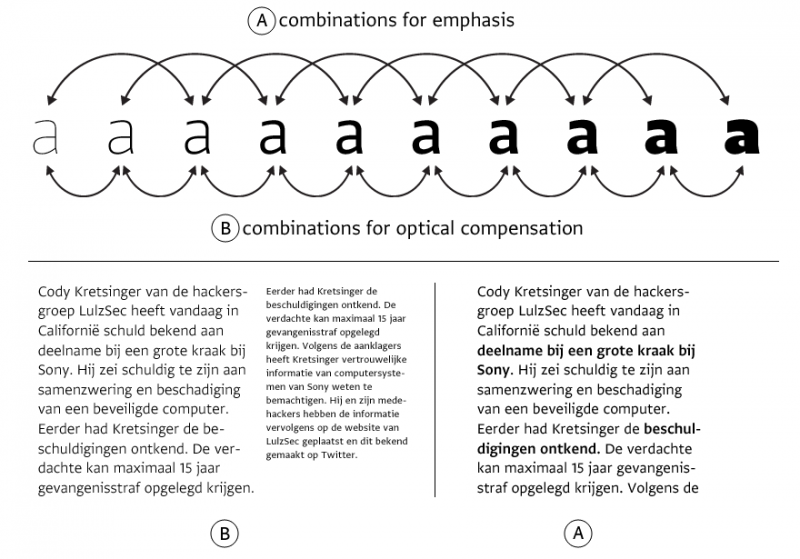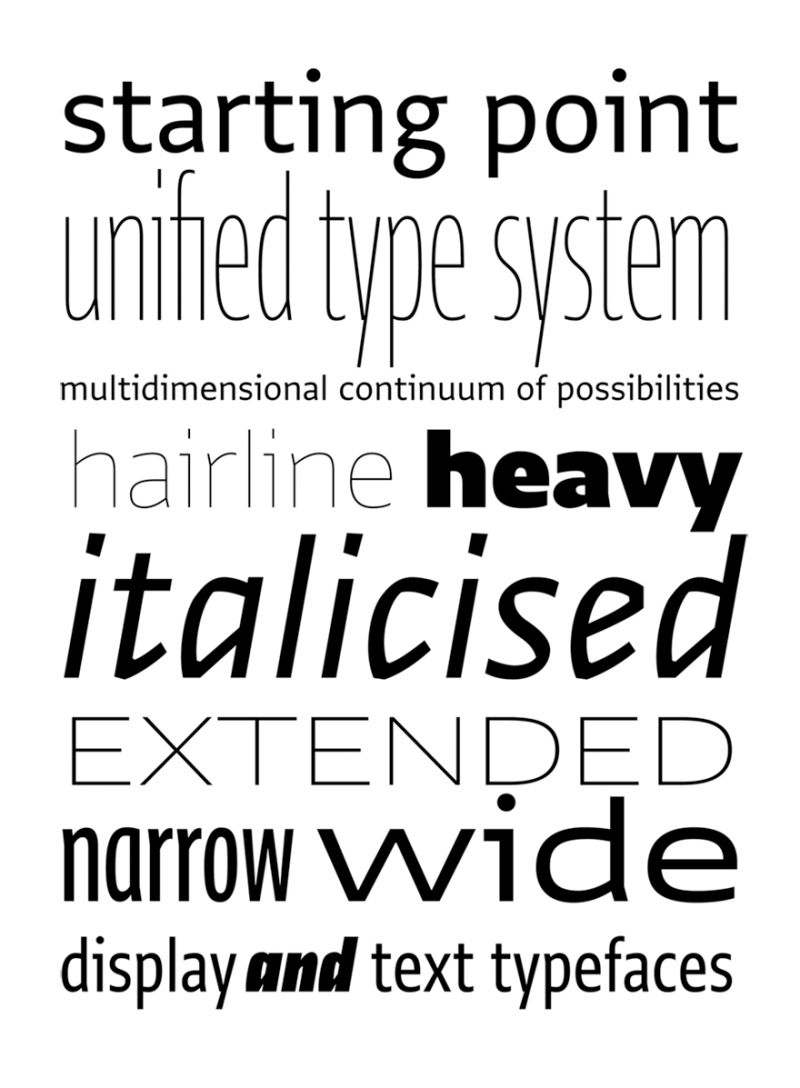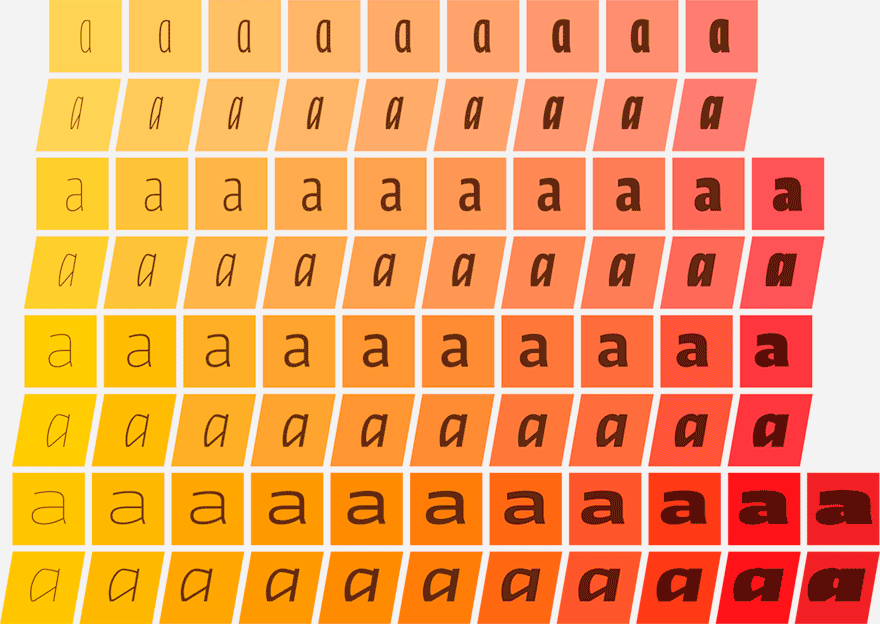
Die Typotheque hat mal wieder aus einer Schrift ein ganzes System entwickelt: Das Greta Sans Typeface System.
Greta Sans erkundet ein mehrdimensionales Kontinuum der Möglichkeiten, die über das Verhältnis von Schnitt und Breite hinaus die Grenzen zwischen Darstellung und Text Schriften verschwimmen lässt. Entstanden ist eine leistungsfähige Tool-Box, die selbst die komplexesten typografischen Situationen bedienen kann.
Greta Sans kommt in 10 Schnitten, die kombiniert mit ihren vier Breiten (Compressed, Condensed, Normal, Expanded) eine enorme Bandbreite vorzuweisen hat.